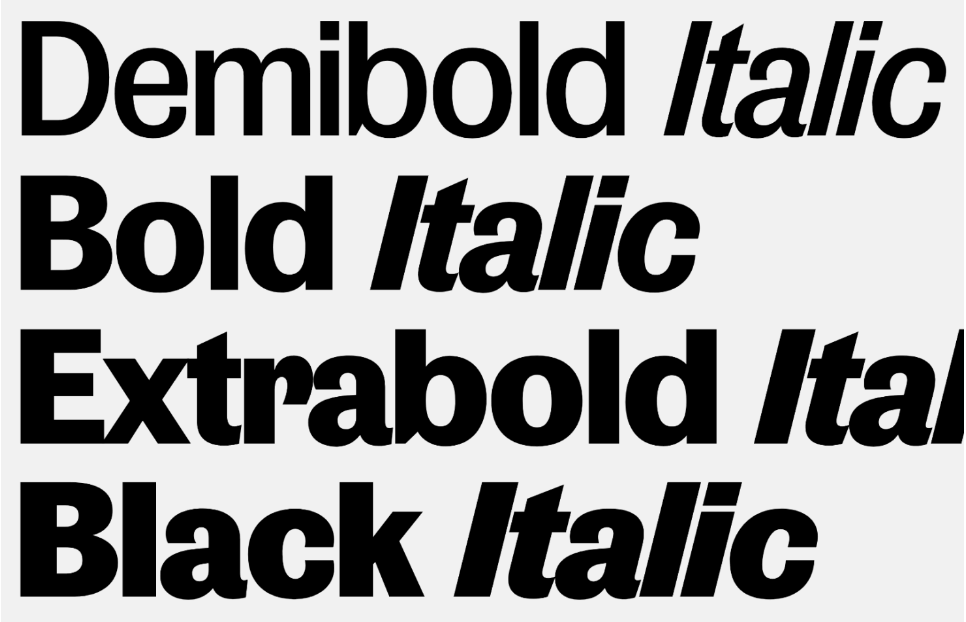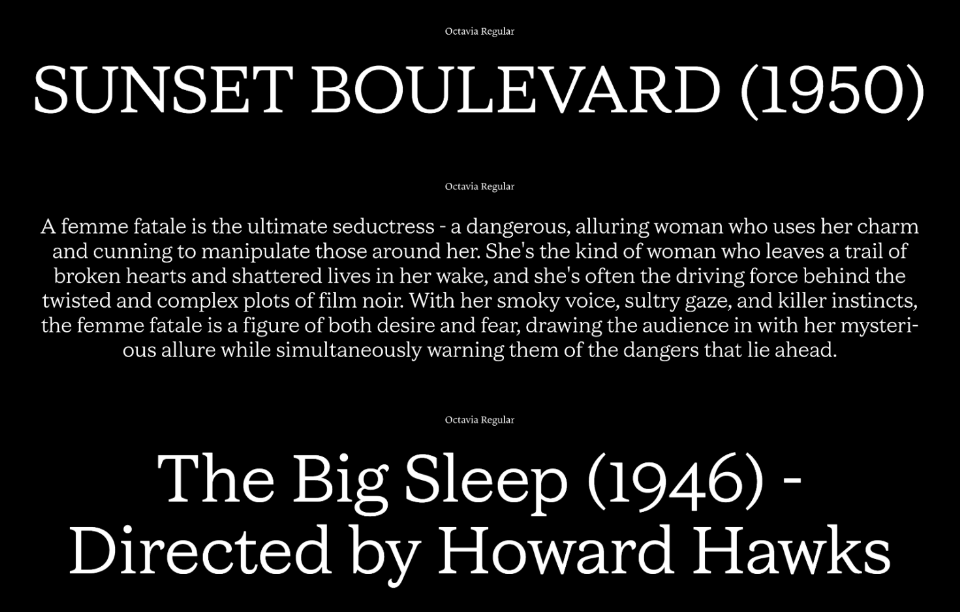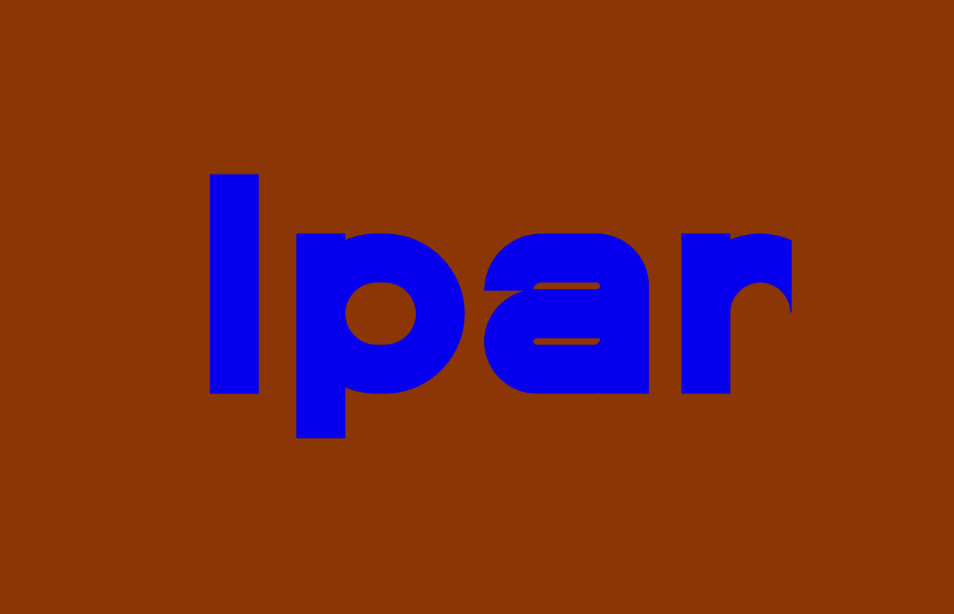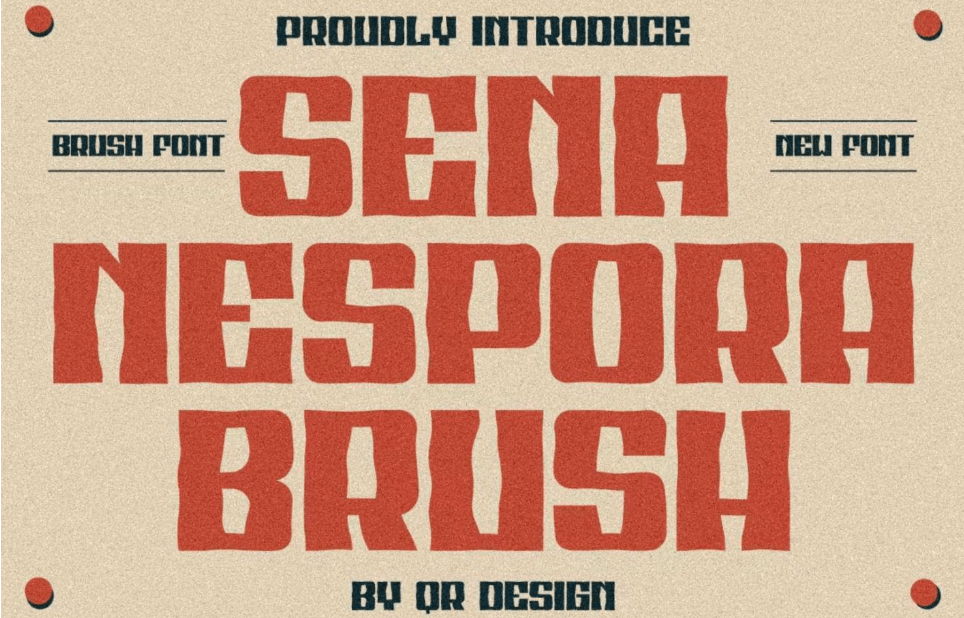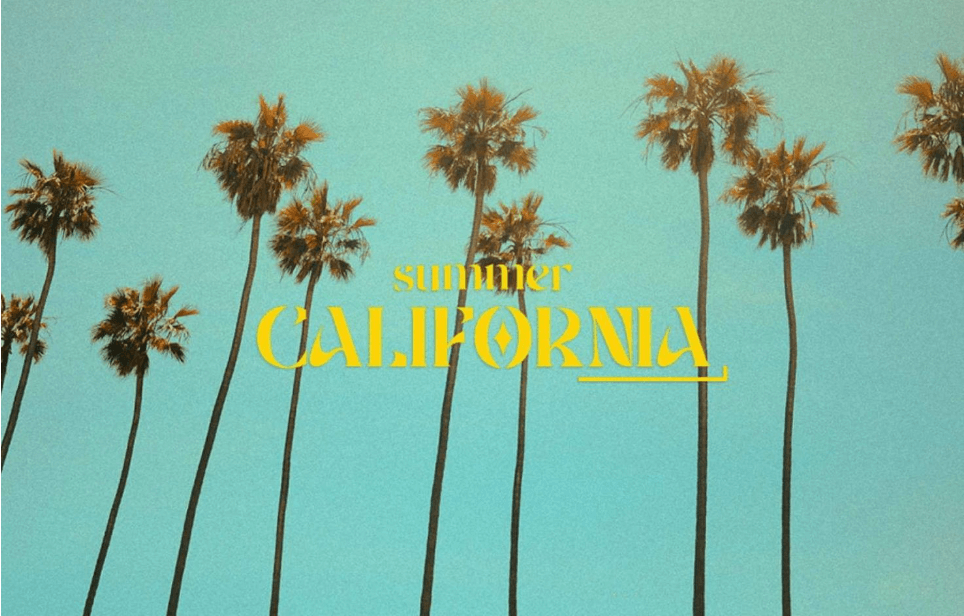
Выбор шрифта — это важный этап при создании сайта. Неправильный выбор может испортить внешний вид вашего сайта и снизить удобство для пользователей. В этой статье мы собрали для вас 12 лучших новых шрифтов, которые уже стали популярными в 2023 году. Шрифты в нашей подборке точно добавят свежести и индивидуальности вашему сайту.
Семейство Publish состоит из нескольких шрифтов: Publish Gothic, Public Sans и Publish Serif. Первоначально этот шрифт был разработан для датской газеты «Dagen», а спустя время он стал доступен для всех. Это универсальный набор шрифтов с разным весом, что делает его идеальным для редакторской работы.
Тида Теп разработала шрифт Octavia в рамках своего дипломного проекта в Type@Cooper в Нью-Йорке. Шрифт вдохновлен названиями нуар-фильмов 1940-х и 1950-х годов, а также финальными титрами.
Шрифт хорошо читается в небольших размерах и прекрасно работает в темном режиме. Шрифт с обычным начертанием доступен уже сейчас, а в скором времени будут доступны 15 дополнительных стилей.
Ipar — это экспериментальный шрифт без оптических исправлений и с нулевой контрастностью. Шрифт стилизован под австрийские уличные и городские знаки, он идеально подойдет для современных и чистых дизайнов. Ipar удобен для дизайна пользовательского интерфейса, и у него есть ряд стилистических альтернатив, которые подойдут для дизайна логотипов.
Sena Nespora Brush — это жирный шрифт с заглавными буквами и интересным волнистым контуром, который выглядит так, будто вы смотрите на текст сквозь воду. Этот шрифт идеально подойдет для создания логотипов и заголовков на веб-сайте.
Matcha — это красивый ретро-трафаретный шрифт с органичными формами. Дизайн букв выглядит очень необычно и немного винтажно — это точно привлечет внимание ваших пользователей. Matcha — это отличный выбор для брендинга и проектов лайфстайл.
At King — это слегка бунтарский шрифт с засечками в винтажном стиле. Шрифт имеет острые засечки и закругленные концы — такой стиль идеально подходит для брендинга или заголовков. Шрифт доступен в семи размерах, а также у него есть версия с переменным шрифтом.